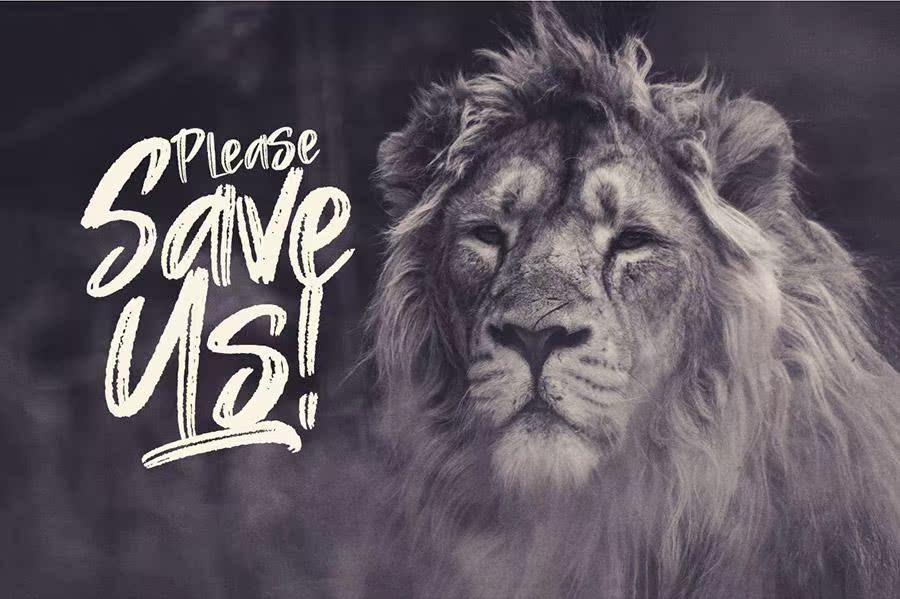
Khurasan回来了,他最新的打字作品RastazScriptFreeFont!此FontIsabrushScriptFontWithReal Hand Brushed Characters。此FontIsabrushScriptFontWithReal Hand Brushed可折叠,但可通过文本格式转换为MakeSitSitedEntity。您可以看到,此FontIsabrushScriptFontWithBranding可用于品牌、徽标。